[자꾸만 눈에 들어와] 1. 달력을 한 장 넘기다 만난 ‘격동고딕’
에디터 눈에 포착된 ‘폰트’의 쓰임을 보여주는 기획연재물
아는 만큼 보인다고 했던가. 폰트 회사에 입사하기 전에는 이렇게 다양한 곳에 폰트가 쓰이는지 몰랐다. 하나씩 알아갈수록 어디를 둘러봐도 폰트가 먼저 눈에 들어온다. 일상에서 만날 수 있는 무궁무진한 폰트의 세계로 함께 떠나보자.
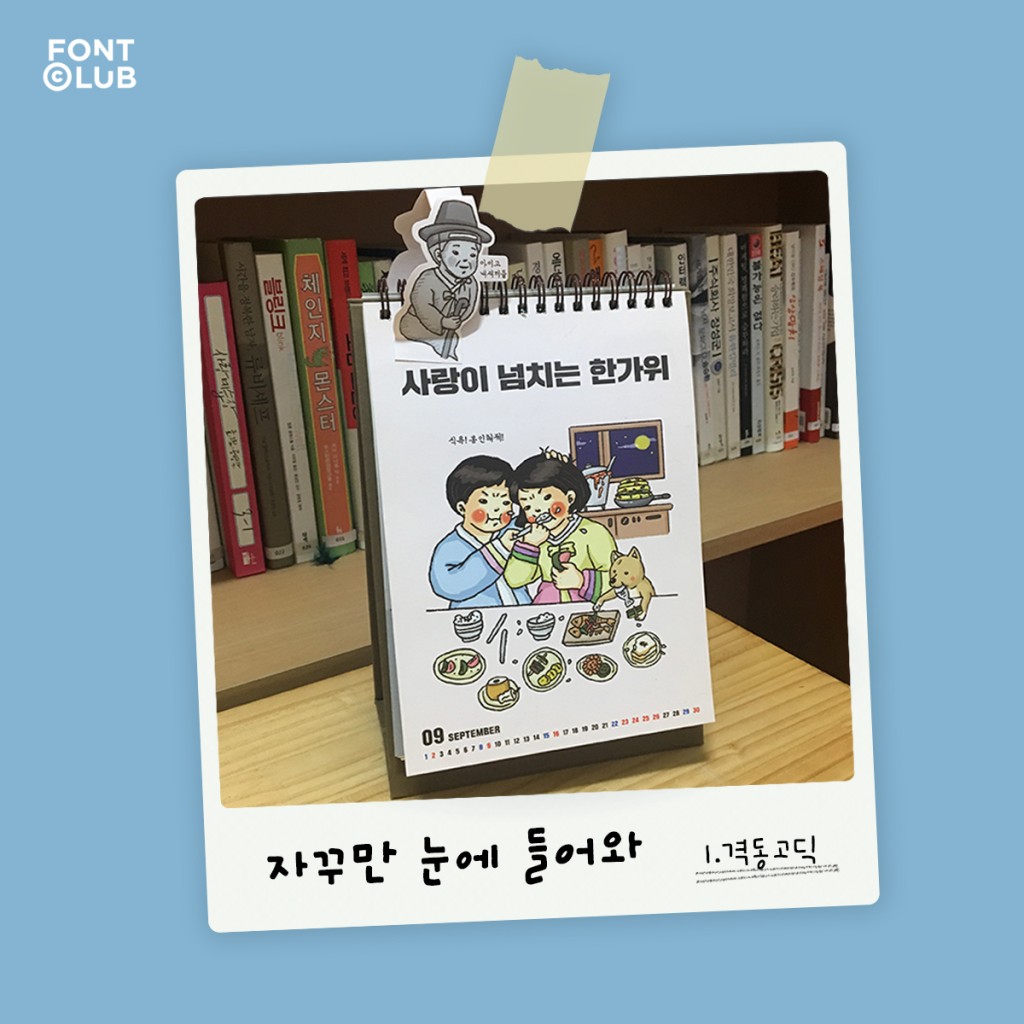
폰트 포착 일시
2018년 9월 3일 오전 9시 40분
폰트명
Sandoll 격동고딕
제작사
산돌커뮤니케이션
폰트 포착 일지
9월의 첫 번째 월요일. 출근하자마자 달력을 한 장 넘겼다.
‘사랑이 넘치는 한가위’. 깜찍한 글씨가 눈에 들어온다.
순간 스친 두 가지 생각. ‘어, 또 격동고딕이네!’
‘아 맞다, 이번 달엔 추석이 있구나!’
추석 연휴를 기다리는 설레는 마음으로 포착한 격동고딕은 눈을 크게 뜨고 둘러보면 어디서든 자주 만날 수 있다.
특유의 카리스마 있는 모습 덕분에 강조하고자 하는 문구에 주로 쓰이는 인기쟁이 폰트이다.
폰트특징
격변하는 70~80년대의 과도기적 시대상을 표현한 폰트. 간판, 포스터, 광고 등 다양한 곳에 사용되고 있다.